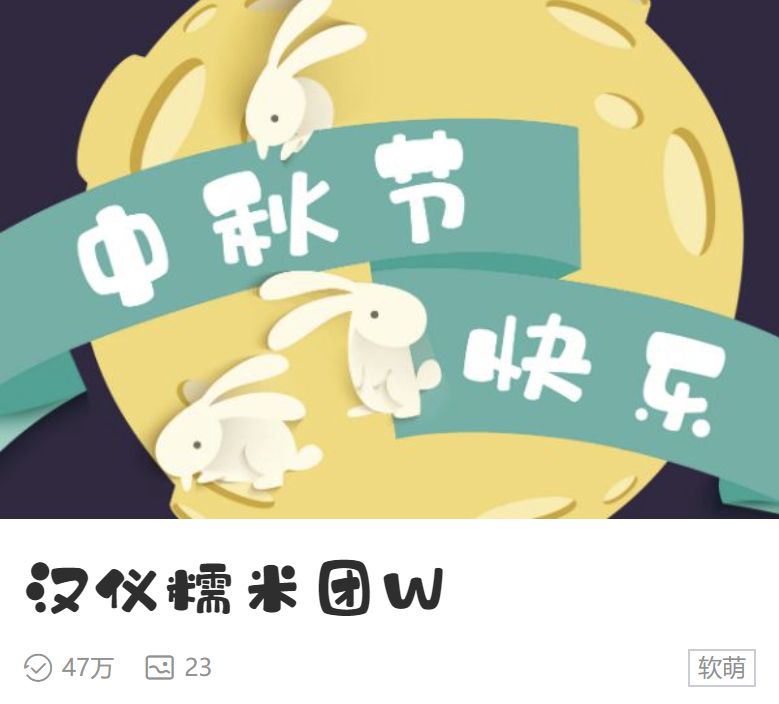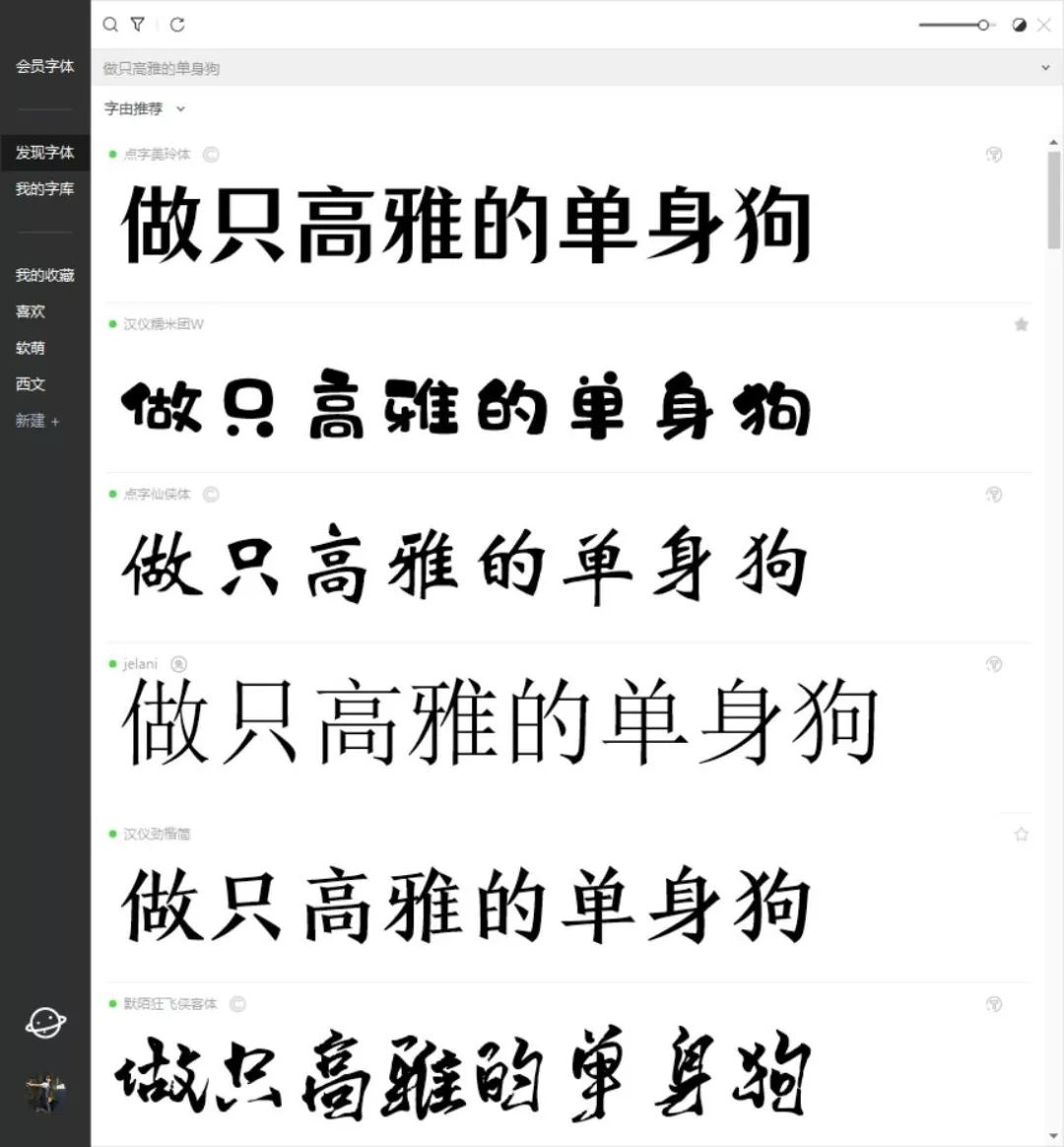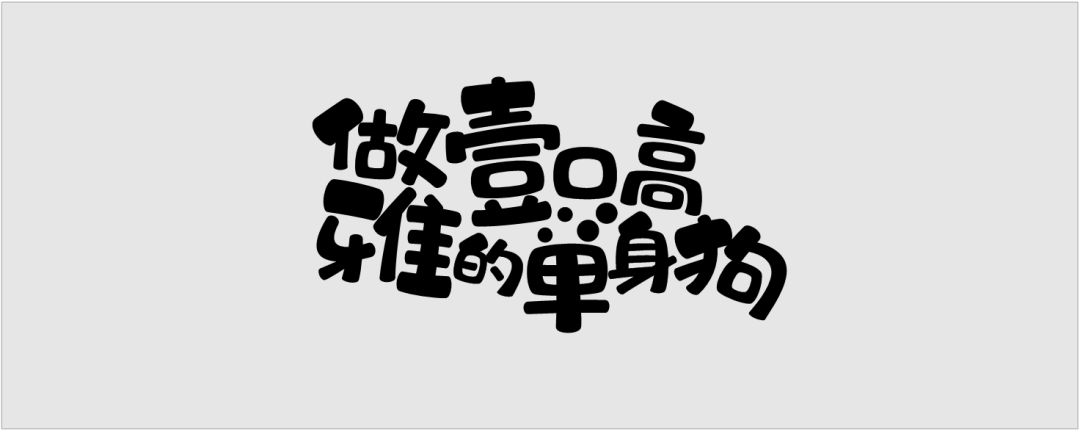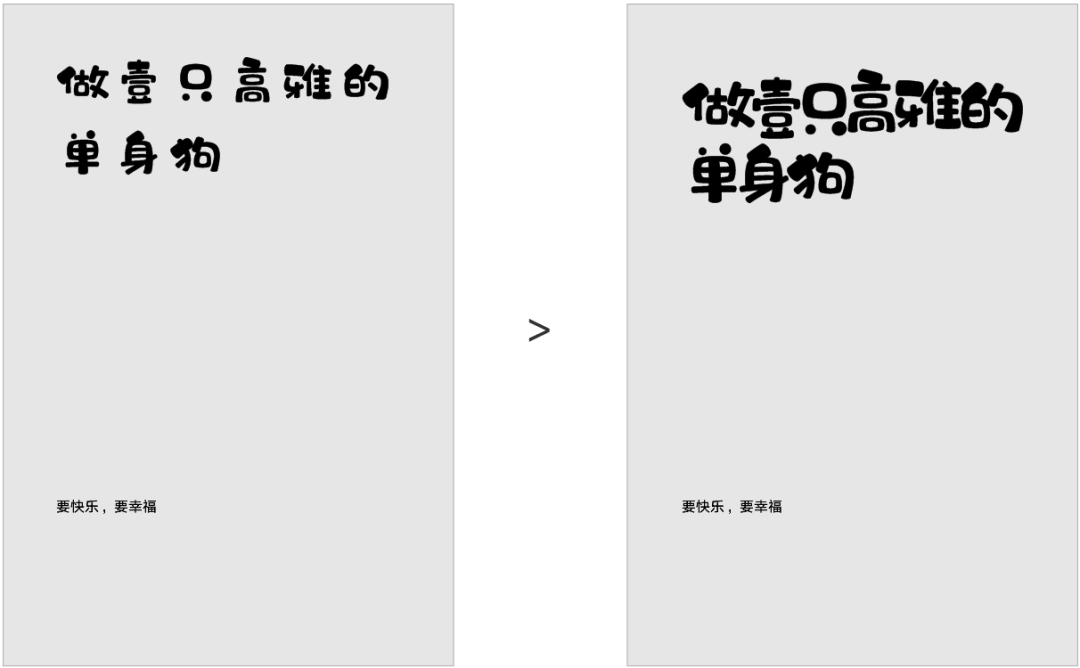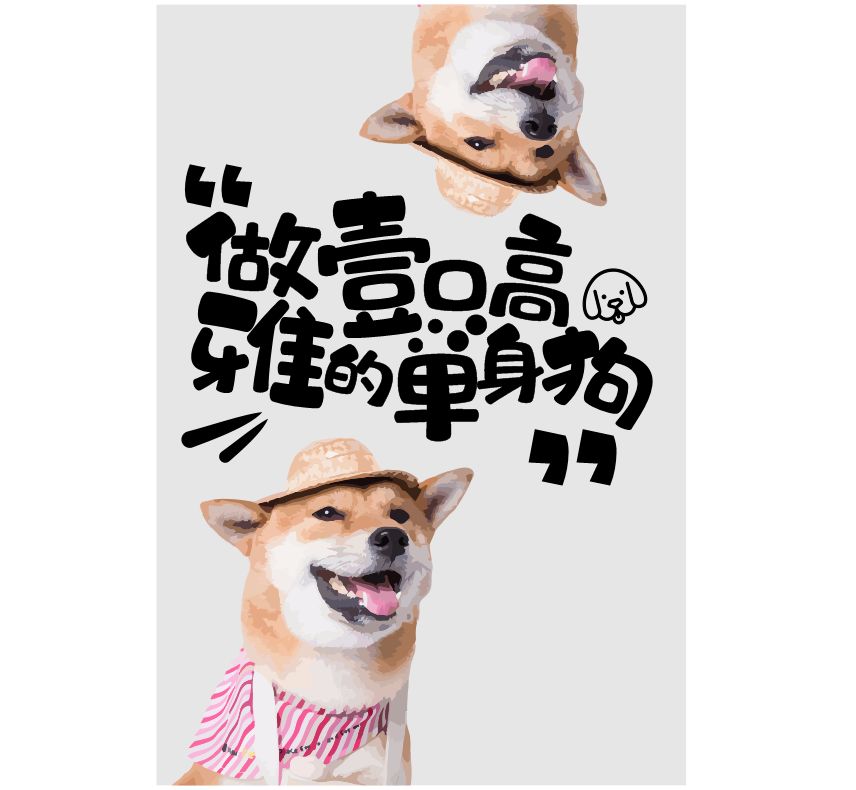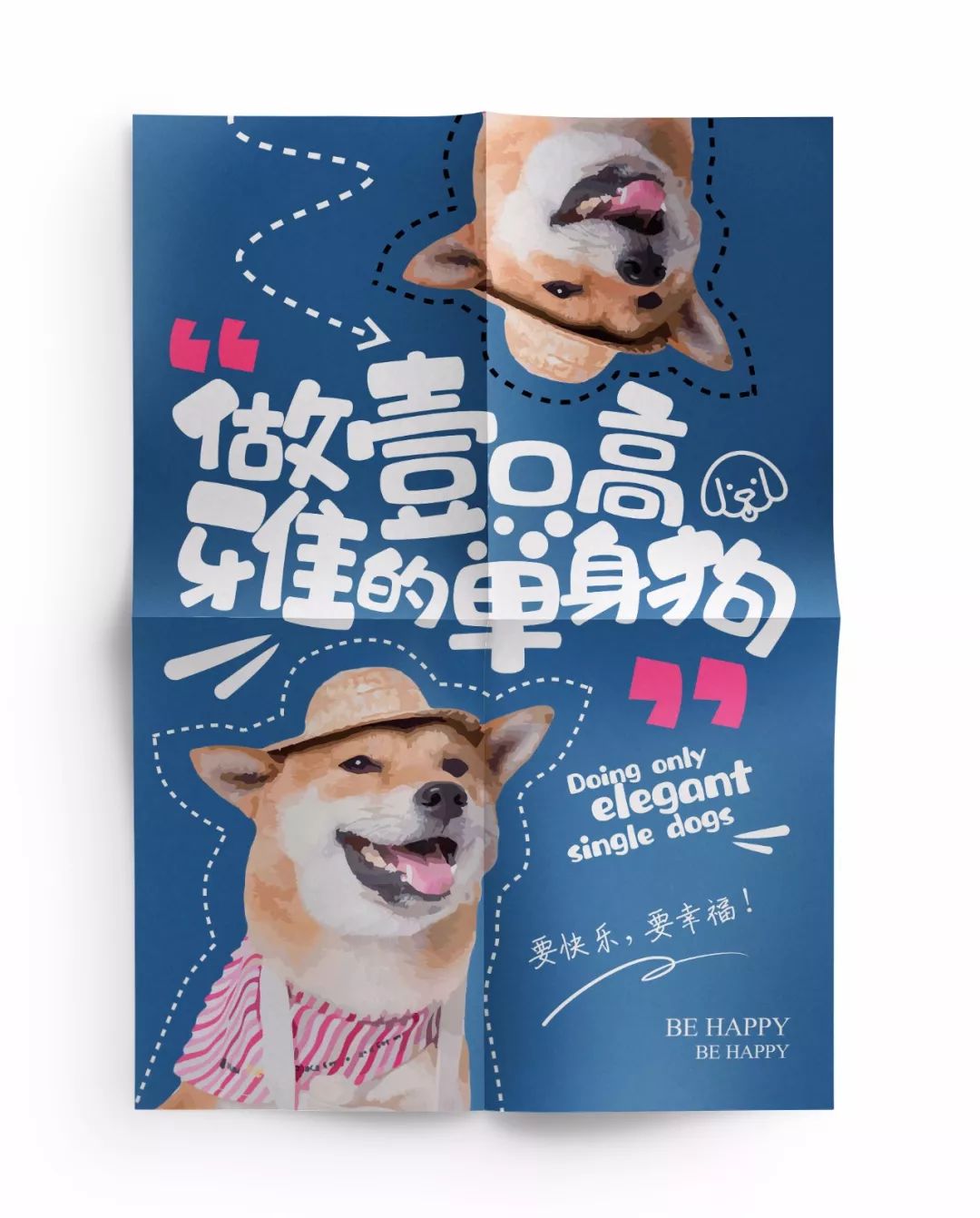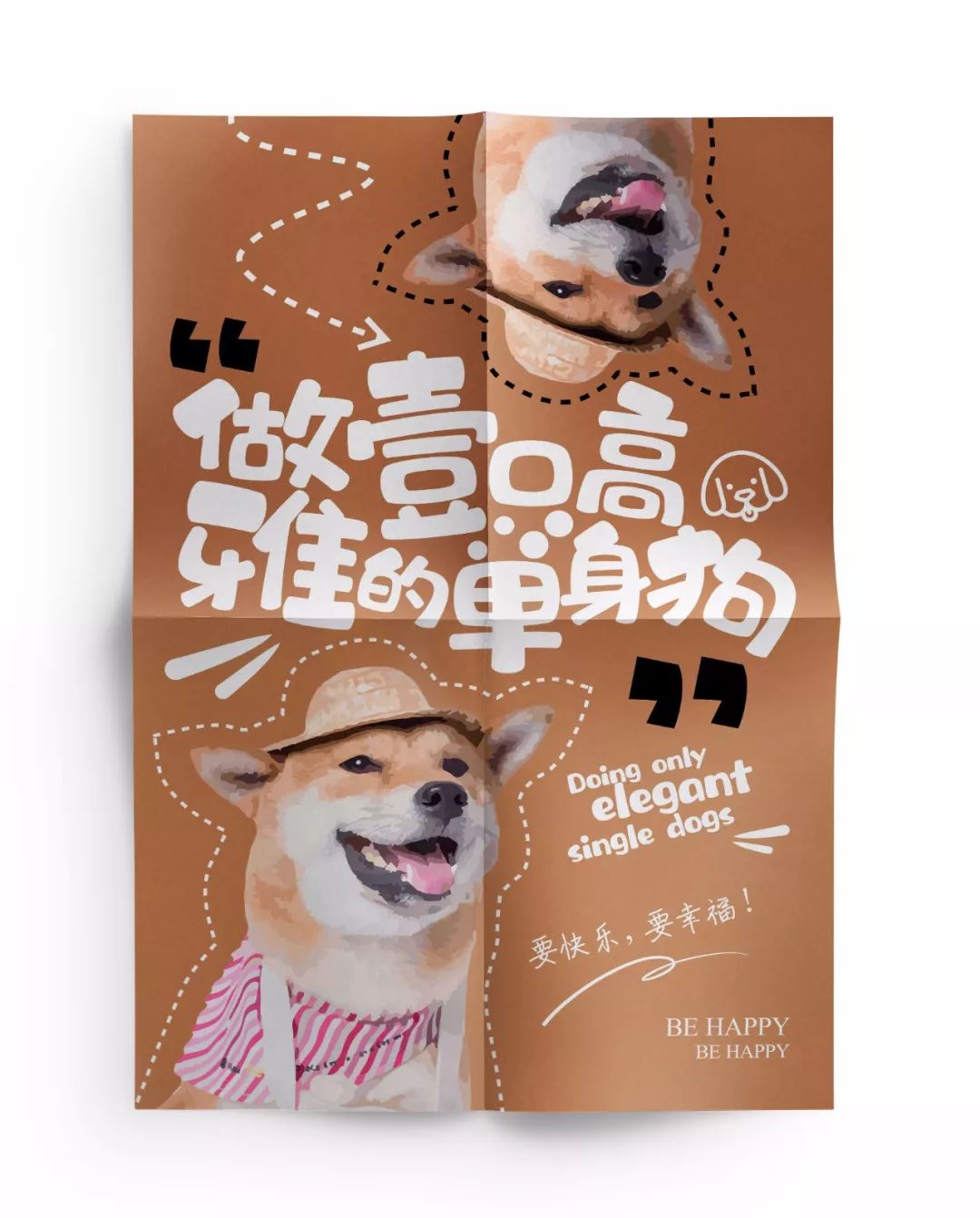
只需五分钟,还原一个有趣的单身狗海报
昨天七夕,有人看了美玲的故事后,酸成了柠檬精……
那柚子今天就来“雪上加霜”一下,做个单身狗主题的海报,哈哈哈~
先选个字体,打开字由,输入文案。
自带软萌气质的汉仪糯米团就很合适~
第一步先把信息排到画面当中,根据层级关系,把主标题断行处理,再放大,增加其视觉占比。
接着用字由,把字体换成汉仪糯米团,并缩减一下字间距。
继续对主标题进行丰富地刻画,使文字之间有个大小对比,并添加旋转效果。
用小狗的标志及符号,进行视觉强化,使画面更加生动有趣。
将主标题放到画面中,开始配合单身狗的元素。
利用重复和对比原则,再复制个单身狗二号。
再添加轮廓线和箭头引导,强化视觉效果。
提取主标题的英文元素,进行符号化处理,放在右下角,形成对比。
最后把剩下的信息放上去,整个画面的文字编排就完成了。
信息编排后我们开始进行配色,可以多做几套,方便选择。